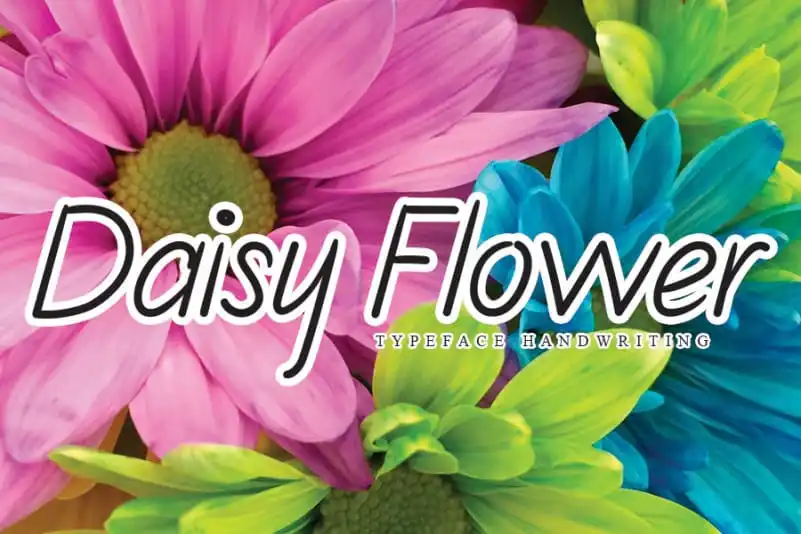
Daisy Flower Handwritten Font – Download Grátis
A Daisy Flower Handwritten Font é uma deliciosa proposta para aqueles que desejam adicionar um toque elegante e criativo às suas criações digitais. Com sua escrita delicada e suave, essa fonte simples traz vida a qualquer projeto visual, tornando-a ideal para um vasto leque de aplicabilidades. Seja você um designer de celebridades ou uma pequena marca local, este fontes é perfeito para criar impressões digitais sofisticadas para as suas postagens nas redes sociais. Além disso, também se destaca em propostas como embalagens de produtos, etiquetas e até mesmo em designs fotográficos e watermarking. Seja qual for o seu objetivo criativo, a Daisy Flower Handwritten Font tem tudo que você precisa para dar vida aos seus projetos digitais de forma única e envolvente. Com sua elegância discreta e estilo autêntico, este fonte é um verdadeiro encanto na era digital, oferecendo a quem o usa uma maneira sutil mas eficaz de destacar seu trabalho.